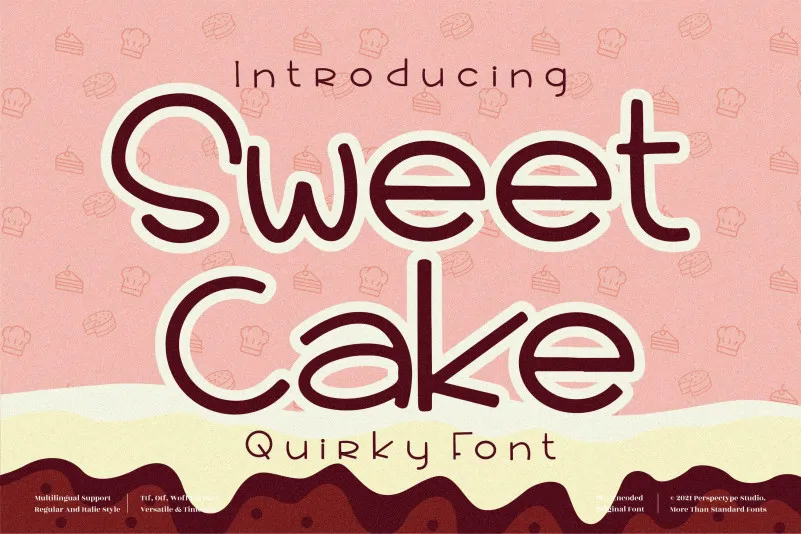
Sweet Cake Font – Fonte Grátis
Sweet Cake Font
A Sweet Cake Font é uma tipografia leve e fina que se destaca por sua escrita cursiva amigável. Perfeito para adicionar algum toque divertido às criações digitais, essa fonte é um ativo valioso para qualquer biblioteca de fontes. Seja você criando um cartão de aniversário personalizado ou desenvolvendo uma identidade visual para sua própria bakery online, essa tipografia vai complementar seu trabalho com perfeição. A Sweet Cake Font foi projetada pelo designer perspectype e é ideal para quem procura adicionar algum toque delicado e divertido a seus designes. Sempre presente na essência da fonte, há um potencial que a torna uma escolha excelente para qualquer aplicação gráfica. Que tal explorar os vários usos desta fonte? Certamente não será um erro!